Font Graffiti việt hoá mang ngôn ngữ thiết kế của văn hóa đường phố vào ấn phẩm kỹ thuật số và in ấn phù hợp với thương hiệu streetwear, sự kiện âm nhạc và nội dung sáng tạo. Bài viết này, In Viva sẽ tổng hợp các font Graffiti Việt hóa đáng tải nhất, kèm hướng dẫn ứng dụng và những lỗi cần tránh.
Không có một font Graffiti duy nhất đáp ứng mọi nhu cầu, mỗi font có phong cách và mức độ hỗ trợ tiếng Việt khác nhau. Bảng dưới tổng hợp các lựa chọn phổ biến nhất trong cộng đồng thiết kế Việt Nam.
Đặc điểm của nhóm font Graffiti
Font Graffiti là nhóm font trang trí lấy cảm hứng từ nghệ thuật đường phố — spray paint, marker và chữ viết tay trên tường. Không phải một font duy nhất mà là cả nhóm phong cách thiết kế có chung nguồn gốc văn hóa.
- Ba phong cách chính: Tag (chữ ký đường phố nét mảnh và nhanh), Bubble (chữ tròn phồng, dễ đọc), Wildstyle (phức tạp, nhiều nét chồng khó đọc nhất nhưng visual mạnh nhất).
- Texture và không hoàn hảo có chủ đích: Nét mực phun, vệt sơn và cạnh chữ không đều là đặc trưng cố ý của nhóm font này không phải lỗi kỹ thuật.
- Hạn chế về bộ ký tự tiếng Việt: Hầu hết font Graffiti gốc chỉ có Latin cơ bản. Các bản Việt hóa cộng đồng bổ sung dấu tiếng Việt nhưng chất lượng Việt hóa không đồng đều giữa các nguồn.
- Chỉ phù hợp cho tiêu đề và điểm nhấn: Font Graffiti không có khả năng đọc tốt ở cỡ nhỏ và không phù hợp cho nội dung dài.
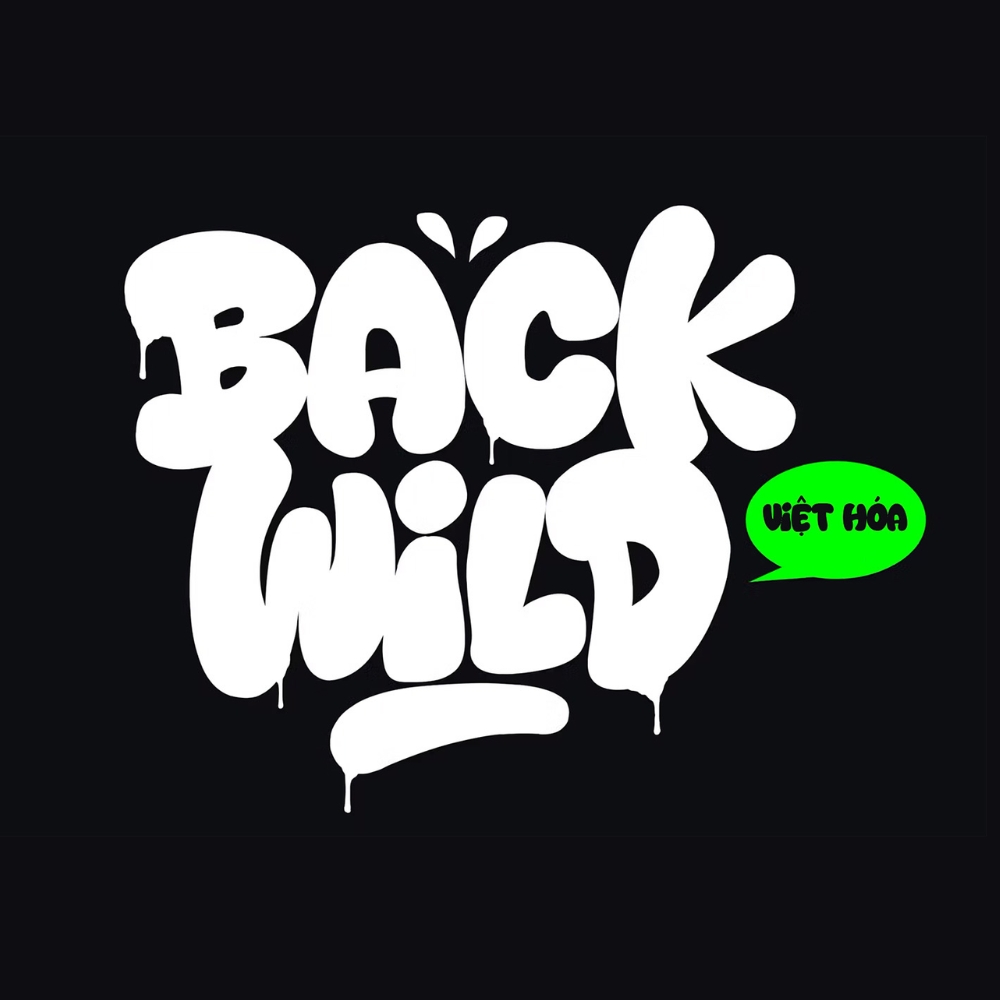
Ứng dụng của font Graffiti trong thiết kế
- Thương hiệu streetwear, thời trang đường phố: Logo, hang tag, packaging và social media content cho các thương hiệu muốn định vị trong không gian urban và youth culture.
- Poster sự kiện âm nhạc, hip-hop, rap: Font graffiti tạo ra ngôn ngữ thiết kế xác thực cho nội dung âm nhạc đường phố — khác biệt rõ ràng so với font thông thường.
- Thumbnail YouTube và nội dung mạng xã hội: Phong cách graffiti thu hút mắt nhìn trong feed đông đúc, đặc biệt hiệu quả cho nội dung gaming, reaction video và content creator trẻ.
- Merchandise và sticker: In trên áo, mũ, tote bag, font Graffiti tạo ra sản phẩm có bản sắc văn hóa đường phố rõ ràng.
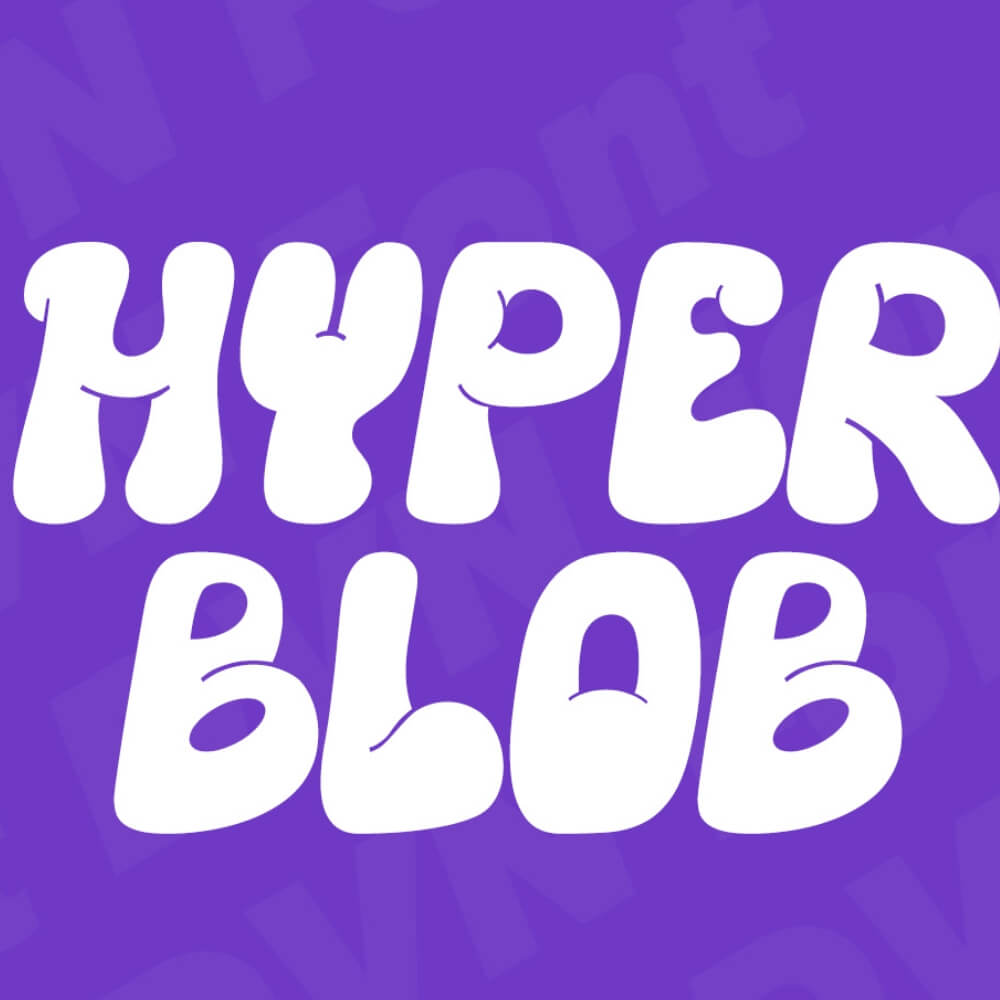
Lỗi thường gặp khi dùng font Graffiti Việt hóa
Dưới đây là các lỗi thường gặp khi dùng font Graffiti Việt hóa mà nhiều người dễ mắc phải, khiến thiết kế mất đi tính thẩm mỹ và không đúng tinh thần đường phố đặc trưng của font.
- Không kiểm tra chất lượng Việt hóa trước khi dùng. Chất lượng Việt hóa của font graffiti rất không đồng đều — một số bản có dấu tiếng Việt được thiết kế cẩn thận, một số chỉ gắn thêm dấu vào vị trí sai hoặc không cân đối. Luôn gõ thử toàn bộ văn bản cần dùng và xem preview trước khi đưa vào thiết kế chính thức.
- Dùng font graffiti cho thương hiệu không phù hợp văn hóa. Font graffiti mang thông điệp văn hóa cụ thể — dùng cho thương hiệu cao cấp, doanh nghiệp truyền thống hoặc sản phẩm gia đình tạo ra sự không nhất quán thương hiệu nghiêm trọng.
- In font graffiti trên nền trắng sạch không có context. Font graffiti cần môi trường thiết kế phù hợp — nền urban, texture tường, màu sắc bold. Đặt trên nền trắng phẳng khiến font trông như placeholder chưa được xử lý.
- Dùng quá nhiều font graffiti khác phong cách trong cùng một thiết kế. Tag + Bubble + Wildstyle trong cùng một poster tạo ra sự hỗn loạn thay vì năng lượng. Chọn một phong cách graffiti duy nhất và nhất quán xuyên suốt thiết kế.
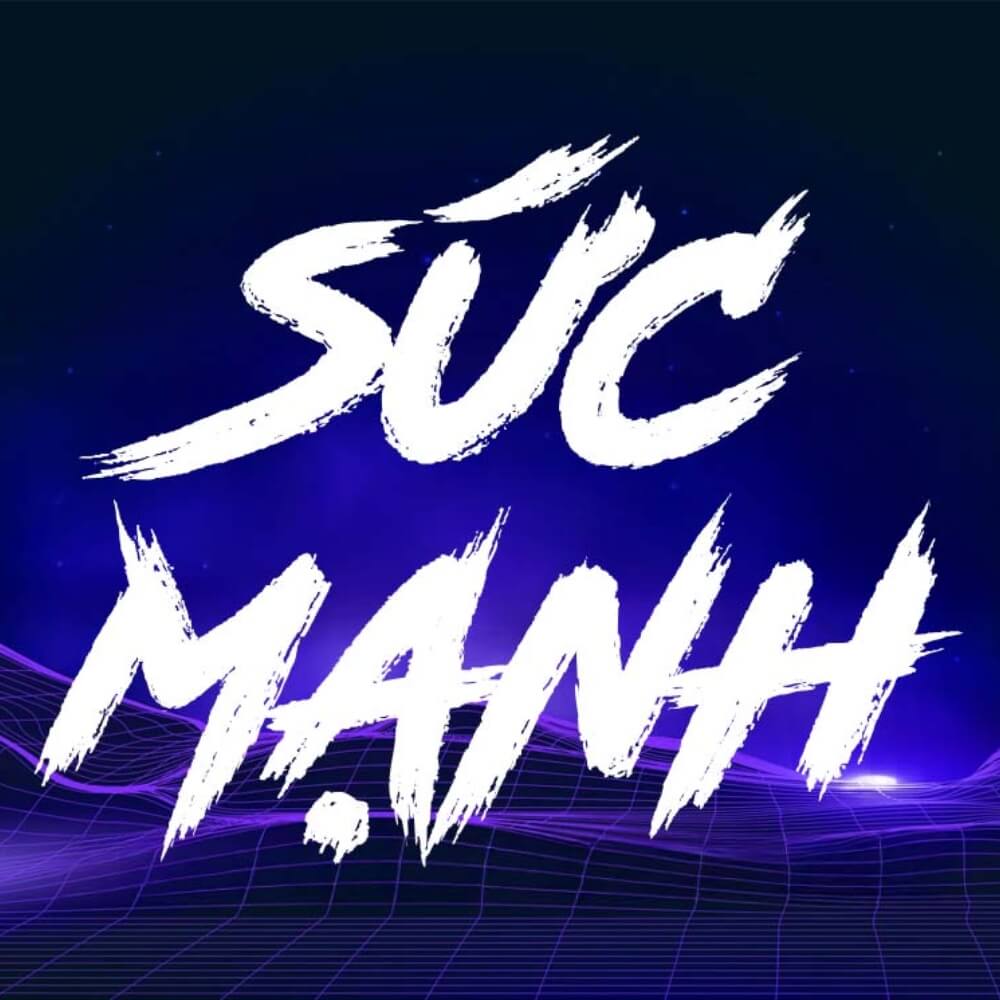
Sprite Graffiti Việt hóa tải ở đâu miễn phí?
Fonttiengviet.com và 1font.com là hai nguồn phổ biến. Tuy nhiên bản quyền thương mại của Sprite Graffiti thuộc tác giả gốc — cần kiểm tra và mua giấy phép nếu dùng cho thương hiệu kinh doanh.
Font graffiti có in được lên vải áo không?
Được. In lụa và in DTG (direct to garment) đều cho kết quả tốt với font graffiti. Cần outline font thành vector trước khi gửi file xưởng in vải để đảm bảo nét chữ chính xác.
Font graffiti nào dễ đọc nhất khi Việt hóa?
Phong cách Bubble graffiti (chữ tròn phồng) dễ đọc nhất khi Việt hóa vì có nhiều không gian để thêm dấu tiếng Việt mà không làm rối bố cục. Wildstyle khó đọc nhất và thường thất bại khi Việt hóa do bố cục quá phức tạp.
Dùng font graffiti cho logo thương hiệu có rủi ro không?